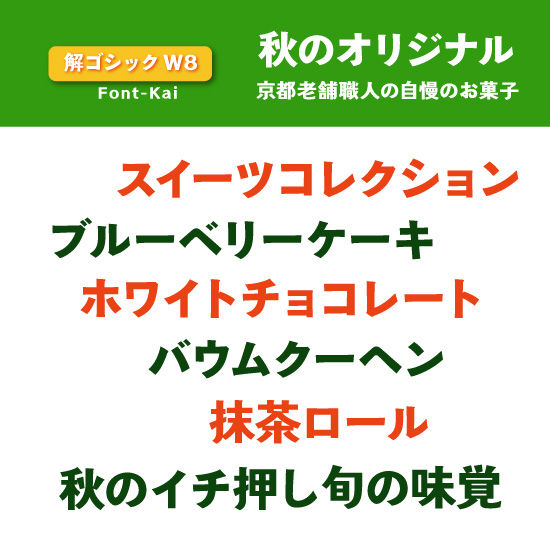
解ゴシック W8
◉「解ゴシック」は活版時代の組版効果を継承しました。各文字のふところなど淀みのない字形空間を図りました。タテ組・ヨコ組ともとても自然な視線誘導で、目にも優しいです。可読性を考慮したハライの曲線と明瞭な文字の空間構成は、ちらつきをおさえた読みやすい文書となります。イラストや写真との相性も良く協調した明瞭な誌面を演出します。